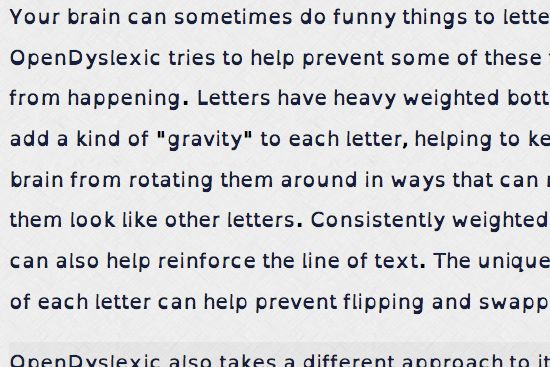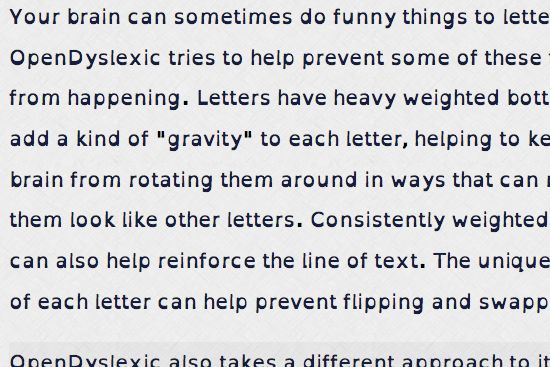
Krój czcionki, który ma pomóc dyslektykom w czytaniu
Dysleksja nadal budzi sporo kontrowersji i podczas gdy dla jednych jest wymówką, żeby przez całe życie nie przyłożyć się do nauki zasad pisowni lub płynnego czytania, dla innych jest to poważne utrudnienie przy pisaniu, czytaniu i komunikacji. Zaburzenia percepcji i pamięci wzrokowej prowadzą między innymi do opuszczania, mylenia i przestawiania liter przy czytaniu i pisaniu. Osoba widzi litery, ale nie jest w stanie dostatecznie szybko skojarzyć ich z dźwiękiem lub odróżniać ich między sobą — po prostu mózg robi ze znakami dziwne rzeczy. Osobom z tym zaburzeniem łatwiej się myśli obrazami, niż słowami, nie mają również problemu z myśleniem lateralnym (w bok, poza przyjętymi ramami), ale przy czytaniu i pisaniu już jest problem (i przy kodowaniu).
Problem z czytaniem może podobno być związany z używanym przez nas alfabetem, który roi się od podobnych do siebie znaków. Aby uczynić je łatwiejszymi do rozróżniania, czyli czytelniejszymi dla osoby ze specyficznymi zaburzeniami percepcji, można stosować odpowiednio zaprojektowane kroje czcionek. Abelardo Gonzalez — na co dzień projektant aplikacji mobilnych — pod koniec zeszłego roku zaczął projektować takie właśnie litery. Brak symetrii i „obciążenie” symulujące grawitację ma pomóc w rozróżnianiu znaków i budzeniu jednoznacznych skojarzeń. Pomysł nie jest nowy i nie jest to pierwszy taki krój, ale jego dzieło — OpenDyslexic — jest jedynym tego typu projektem otwartoźródłowym.
Gonzalez współpracuje z osobami mającymi zaburzenia postrzegania liter i na podstawie ich uwag udoskonala swój projekt. W planie jest między innymi opracowanie kerningu i dalsze poszerzanie zestawu znaków (polskich znaków diakrytycznych na razie brak). OpenDyslexic został już wykorzystany między innymi w przeglądarce openWeb dla iOS, choć chyba najwięcej rozgłosu przysporzyło mu dołączenie do Instapaper. Sony i Amazon rozważają dołączenie go do swoich czytników e-booków, Google również przygląda się projektowi.